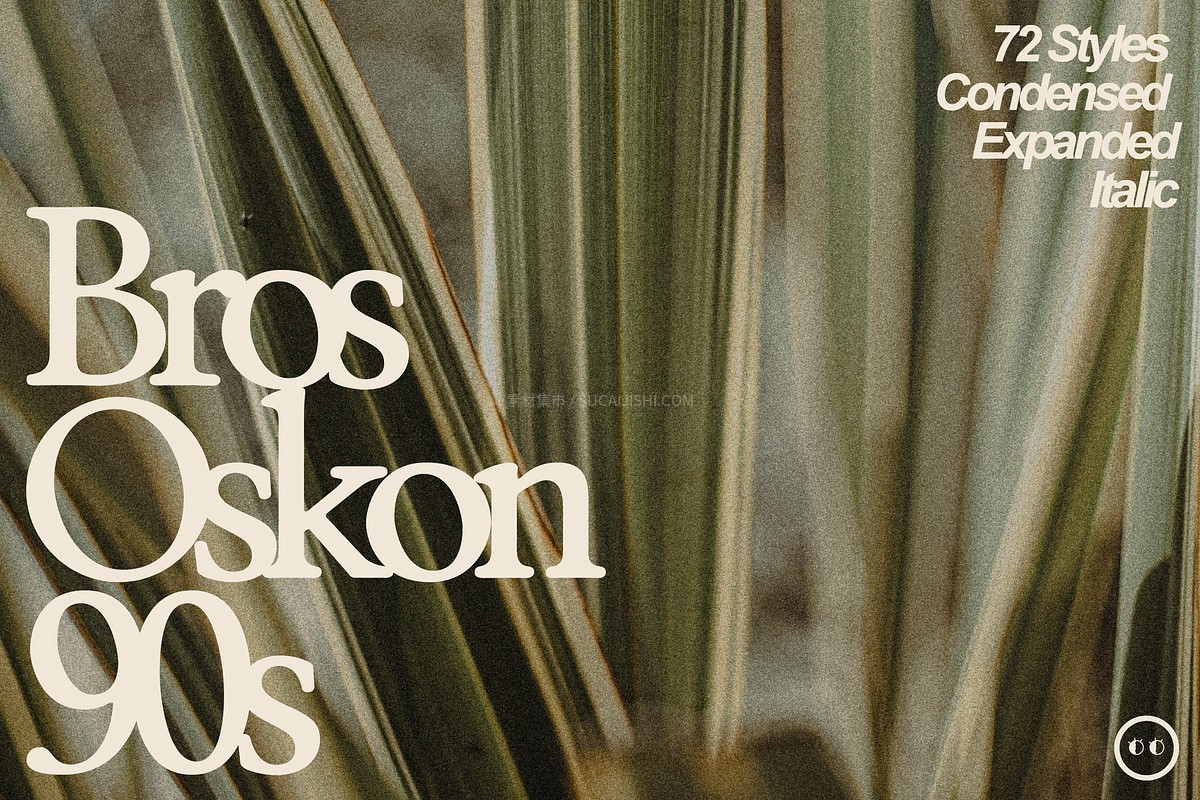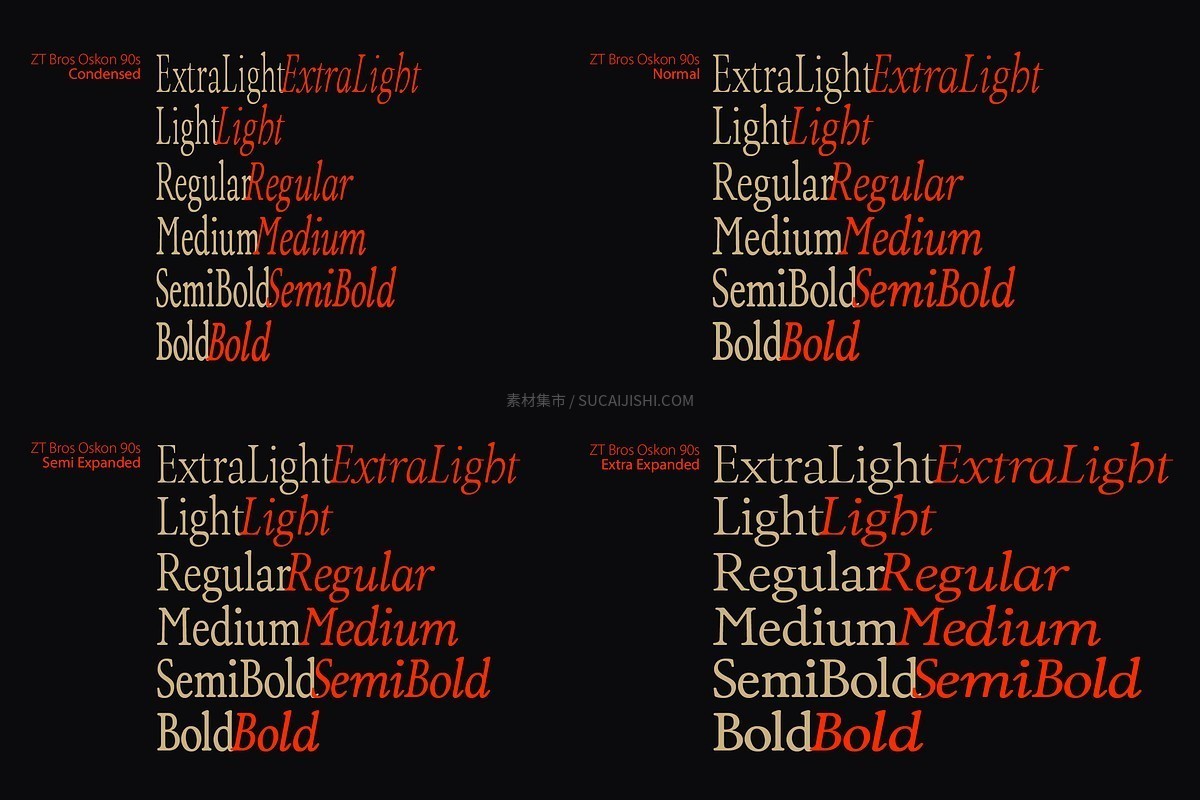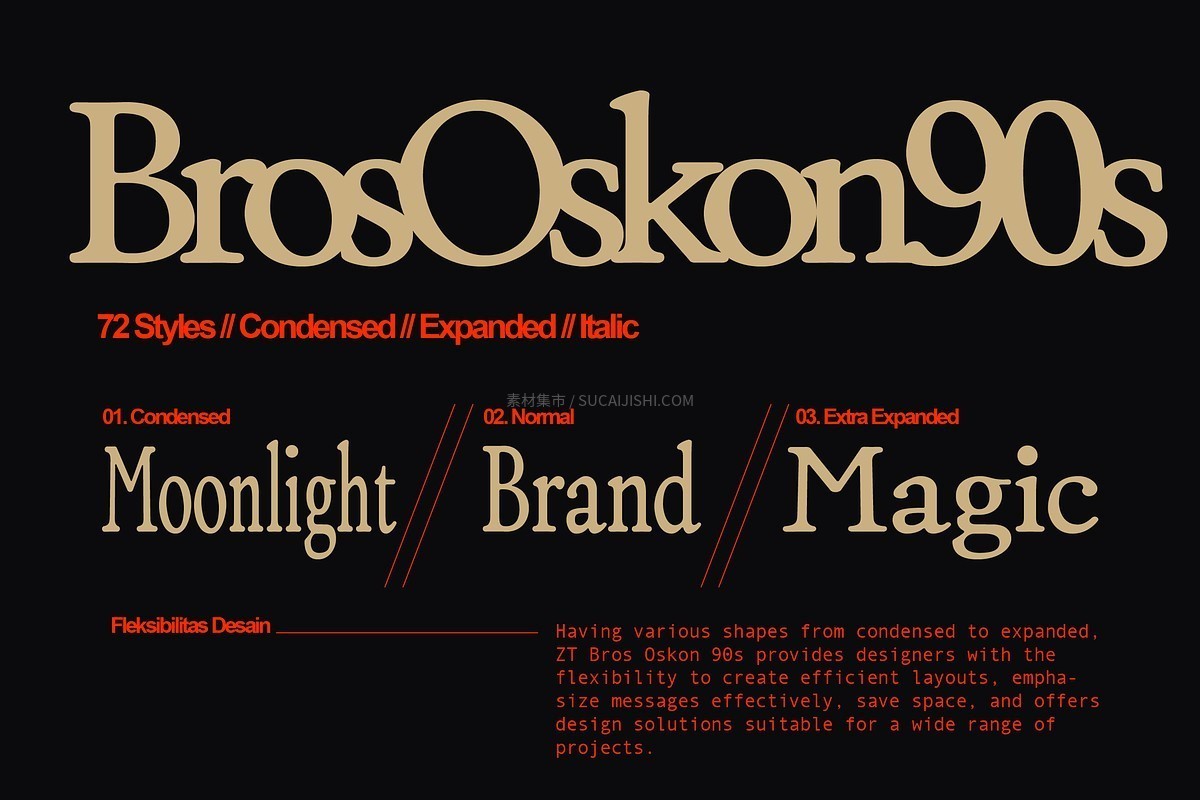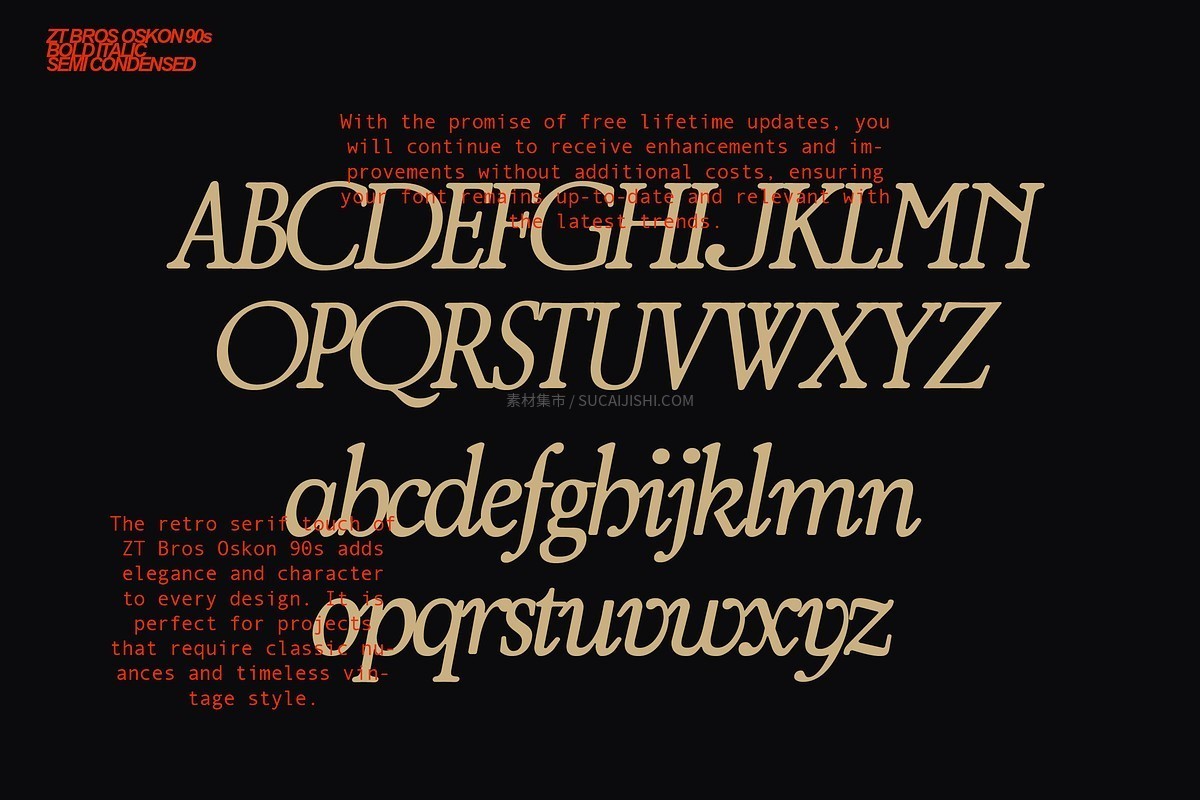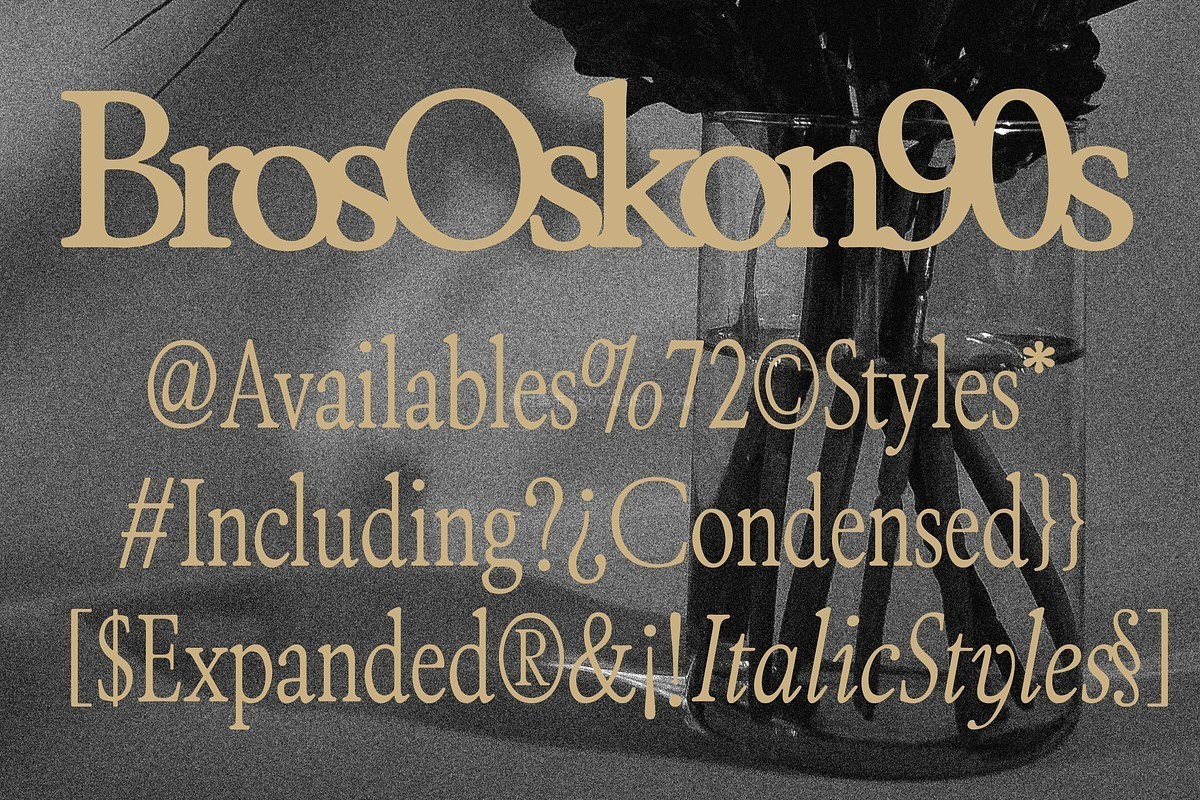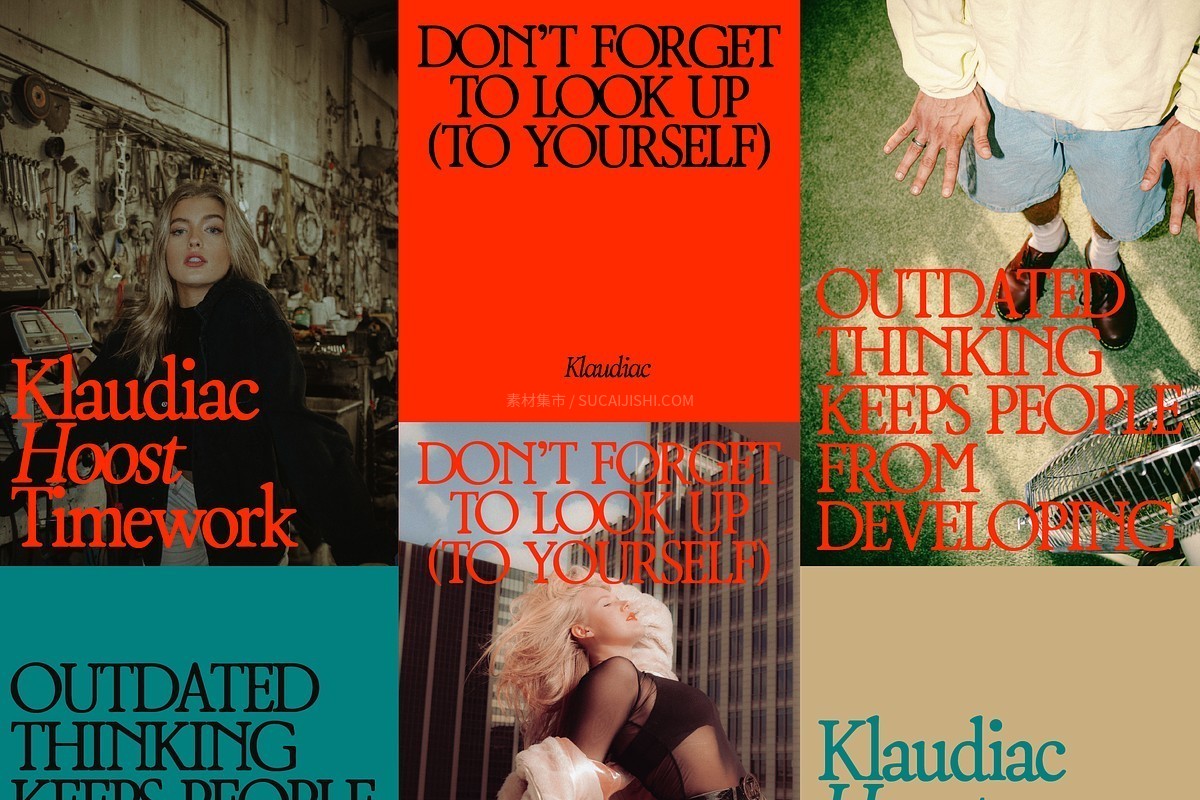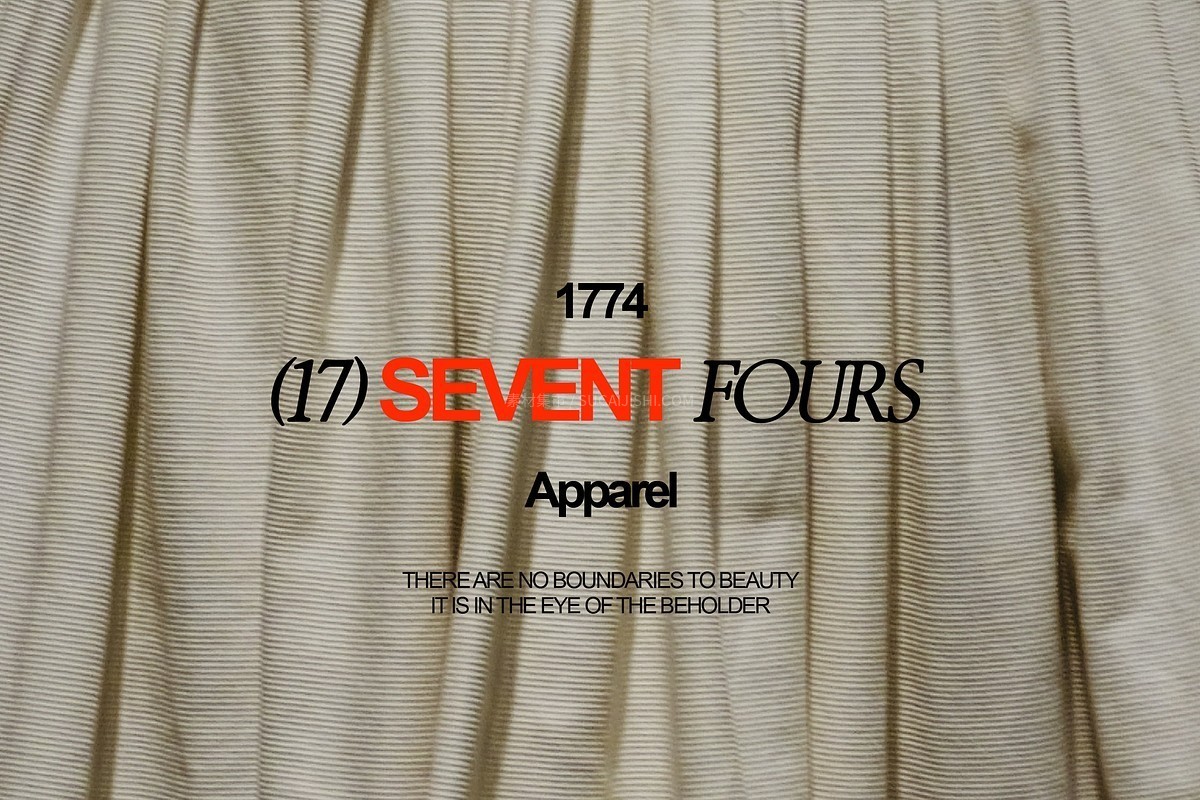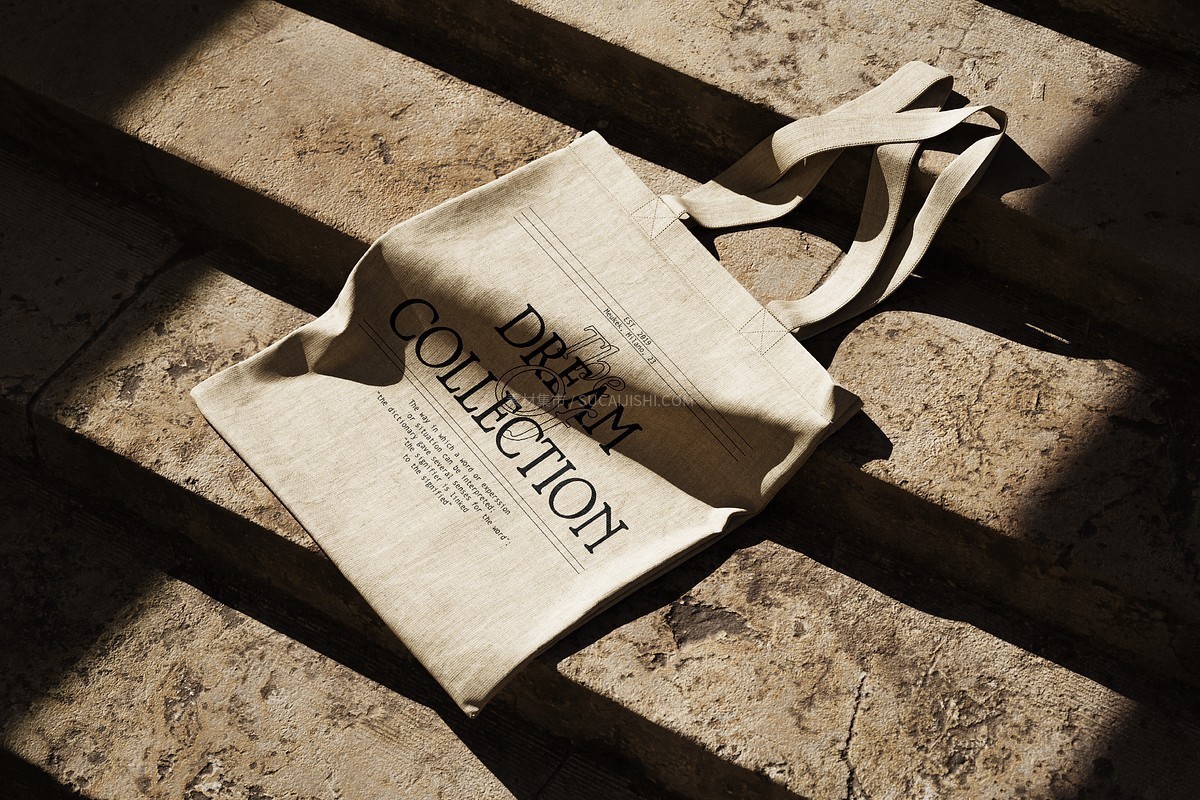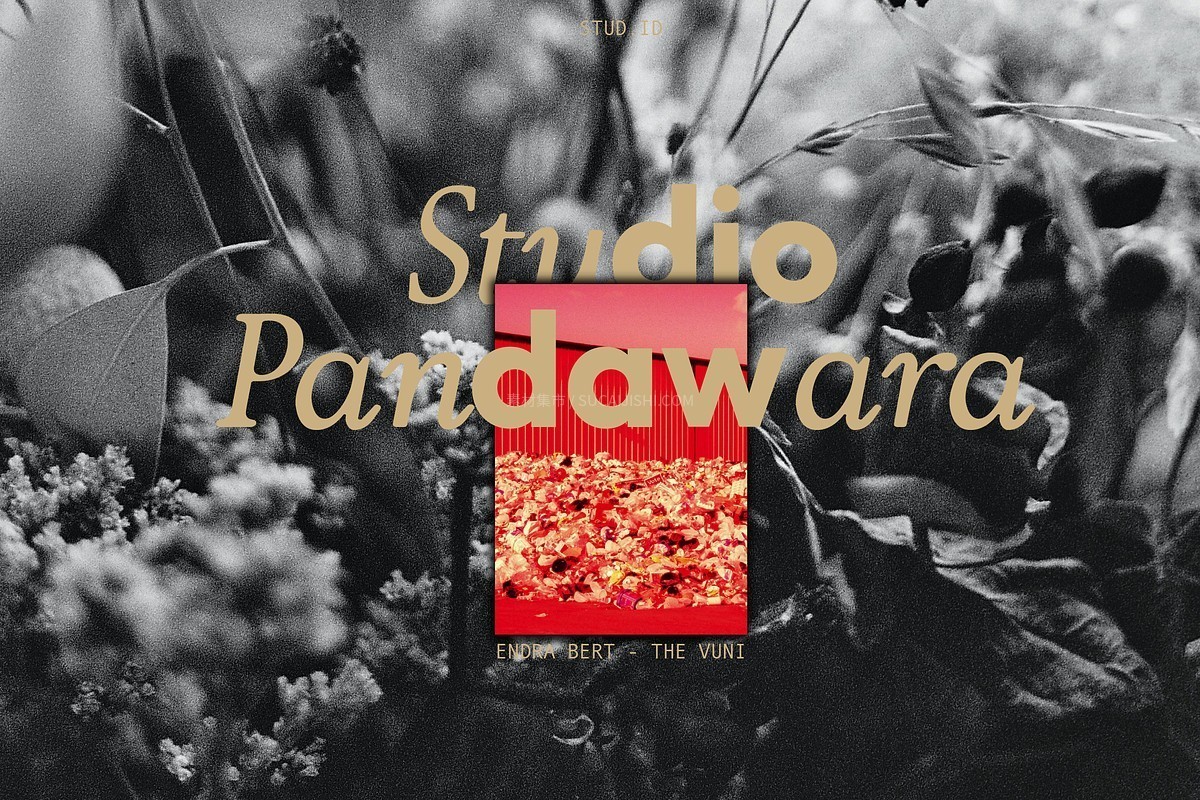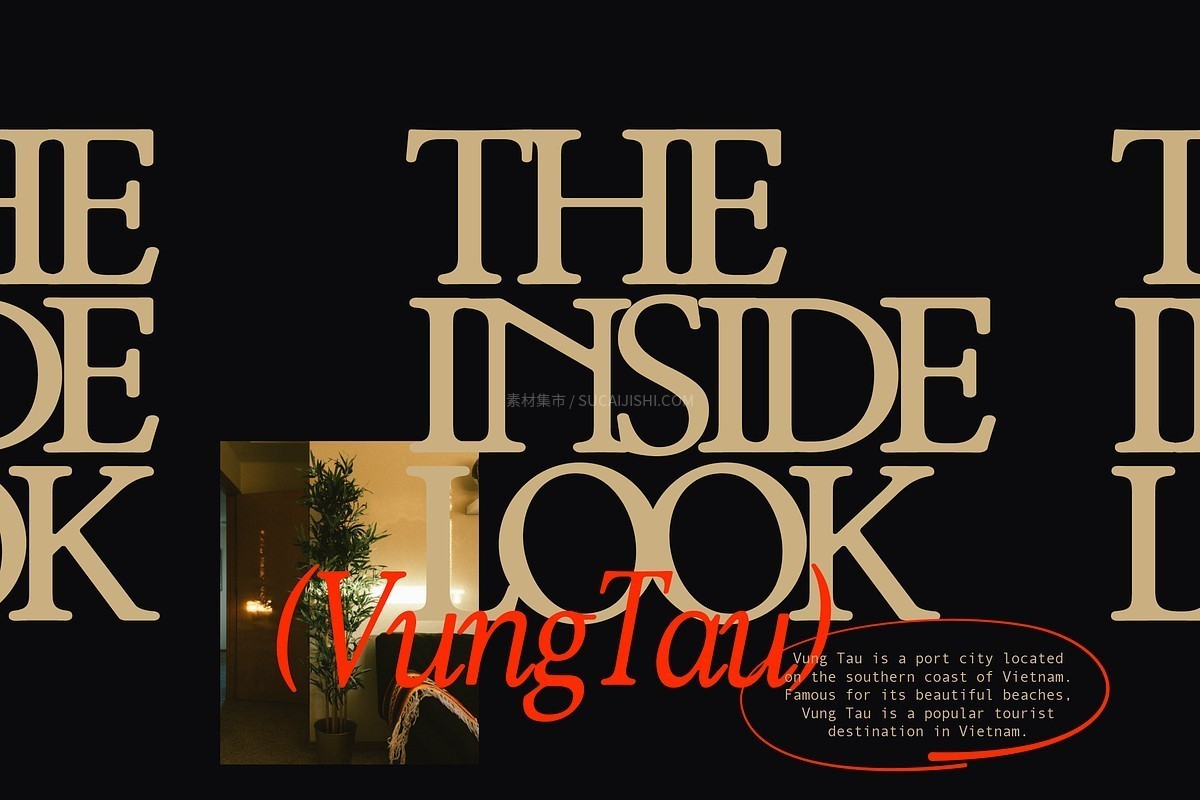
ZT Bros Oskon 90s 复古优雅衬线字体完整版
ZT Bros Oskon 90s 是一款引人入胜的视觉杰作,它巧妙地将 20 世纪 90 年代的经典复古魅力与现代排版气息融为一体。这款字体拥有无与伦比的衬线优雅感,每个字符都经过精心雕琢,营造出令人着迷的怀旧氛围。
该字体家族极其庞大,提供多达 72 种字形变化,涵盖了从锐利的窄体(Condensed)、优美的宽体(Expanded)到迷人的斜体(Italic)。同时包含从特细(Extra Light)到粗体(Bold)的 6 种字重,极高的灵活性让你可以轻松驾驭任何具有挑战性的创意设计,为作品注入灵魂。